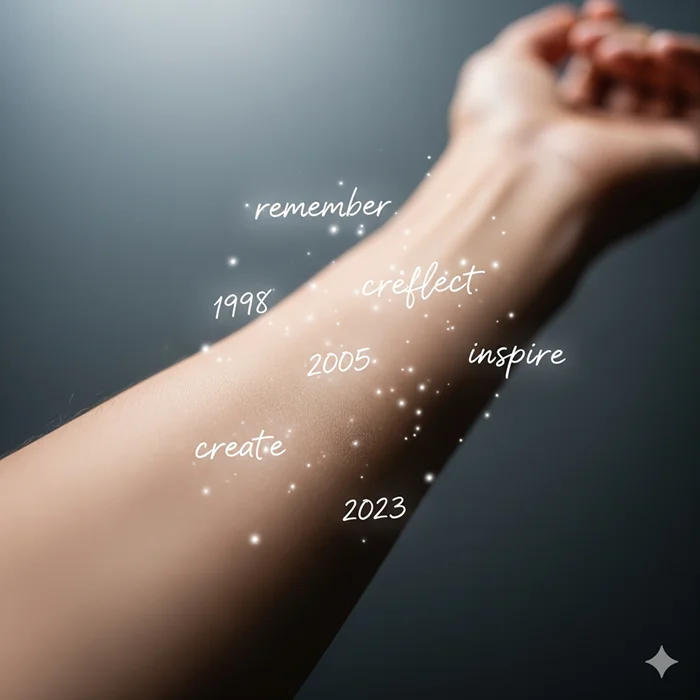
Tattoo SchriftGenerator
Einzigartige Schriftarten für Deko Ideen
Die Wahl der perfekten Tattoo schrift generator ist eine der wichtigsten Entscheidungen bei der Gestaltung Ihres Tattoos. Schriftart, Stil und Design der Schrift verraten viel über Sie. Egal, ob Sie einen Tattoo-Schriftzug oder eine minimalistische Schrift planen – ein Font-Generator hilft Ihnen, die perfekte Schriftart für Ihr Tattoo zu finden. Dieser Leitfaden führt Sie durch die Auswahl der besten Tattoo-Schriftarten, gibt Tipps zur Verwendung eines Font-Generators und zeigt Ihnen, wie Sie einzigartige Schriftzüge erstellen, die wirklich zu Ihnen passen.
Was ist Tattoo Schrift Generator und warum ist sie wichtig?
Die Tattoo-Schrift bezeichnet den Stil oder die Schriftart des Textes, der in einem Tattoo-Design verwendet wird. Ob Zitat, Name oder Datum – die gewählte Schriftart hat einen großen Einfluss auf die Gesamtästhetik des Tattoos genau wie Instagram Schrift. Von kräftigen, dramatischen Buchstaben bis hin zu eleganter Schreibschrift – jeder Stil vermittelt etwas anderes. Es ist wichtig, eine Schrift zu wählen, die zu der Botschaft oder Emotion passt, die Sie vermitteln möchten.
Arten beliebter Tattoo Schriftarten (Fonts)
1. Cursive Tattoo Schrift (Schreibschrift)
Schreibschriften wie Schreibschrift sind eine zeitlose Wahl für Tattoos. Sie verleihen dem Design einen Hauch von Eleganz und Fluss und eignen sich daher ideal für Namen, Zitate oder bedeutungsvolle Sätze. Die durchgehenden Striche handschriftlicher Schriftarten verleihen dem Tattoo eine persönliche, intime Note.
2. Fette und klassische Schriftzüge
Wenn Sie ein Tattoo mit einem besonderen Akzent suchen, sind kräftige Schriftzüge oder Schriftarten mit dicken Linien perfekt. Diese Schriftarten werden oft für aussagekräftige Botschaften oder kurze Zitate verwendet. Die scharfen, kräftigen Linien sorgen dafür, dass das Design auch nach Jahren noch hervorsticht.
3. Vintage- und Old-English-Schriftarten
Für alle, die klassische, zeitlose Looks lieben, sind Old-English oder Vintage-Schriftarten eine ausgezeichnete Wahl. Sie vermitteln ein Gefühl von Geschichte und verleihen dem Tattoo oft ein traditionelles Flair. Diese Schriftart eignet sich gut für Namen, Daten oder Familienwappen.
4. Moderne und minimalistische Schriftarten
Wenn Sie klare Linien und eine moderne Ästhetik bevorzugen, sind minimalistische Schriftarten die beste Wahl. Diese Schriftarten zeichnen sich typischerweise durch scharfe, gerade Linien und einfache Kurven aus, wodurch sie leicht lesbar sind und sich perfekt für alle eignen, die einen modernen Look wünschen.
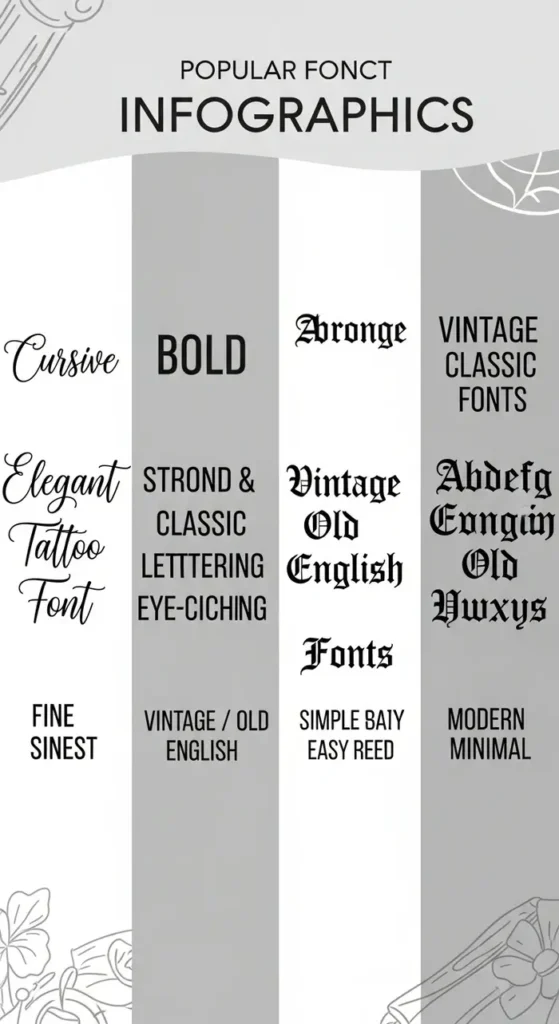
So finden Sie die richtige Tattoo-Schrift mit einem Schriftgenerator
Die Wahl der perfekten Tattoo-Schrift kann eine Herausforderung sein. Unser Online Schriftgenerator vereinfacht den Prozess. So erstellen Sie mit einem Tattoo-Schriftartengenerator das perfekte Tattoo-Design:
1. Verschiedene Schriftarten entdecken
Entdecken Sie zunächst verschiedene Schriftarten und finden Sie heraus, welche Ihnen am besten gefällt. Mit einem Schriftarten-Generator können Sie verschiedene Stile ausprobieren – von handgeschriebenen Schriftarten bis hin zu fetten, modernen Handschriften. Ob Sie Zahlen für ein Datum oder eine schöne Schriftart für einen Namen suchen – mit dem Generator können Sie visualisieren, wie verschiedene Schriftarten auf Ihrer Haut wirken.
2. Design anpassen
Sobald Sie einen Stil gefunden haben, der Ihnen gefällt, können Sie ihn im nächsten Schritt anpassen. Viele Generator-Tools ermöglichen es Ihnen, den Abstand, die Größe und sogar die Form des Textes anzupassen, um Ihr gewünschtes Design zu optimieren. Sie können mit verschiedenen Effekten experimentieren, bis Sie den gefunden haben, der am besten zu Ihrem Text passt.
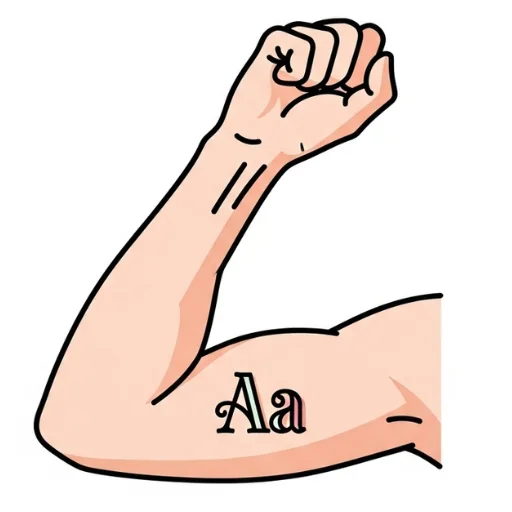
3. Vorschau der Tattoo Schrift Generator
Einer der größten Vorteile eines Schriftgenerators ist die Vorschau Ihres Tattoos vor dem Stechen. Indem Sie sich vorstellen, wie die Schrift auf Ihrer Haut aussehen wird, können Sie bei Bedarf Anpassungen vornehmen, um sicherzustellen, dass das endgültige Design genau Ihren Vorstellungen entspricht.
Best Practices für die Auswahl von Tattoo-Schrift
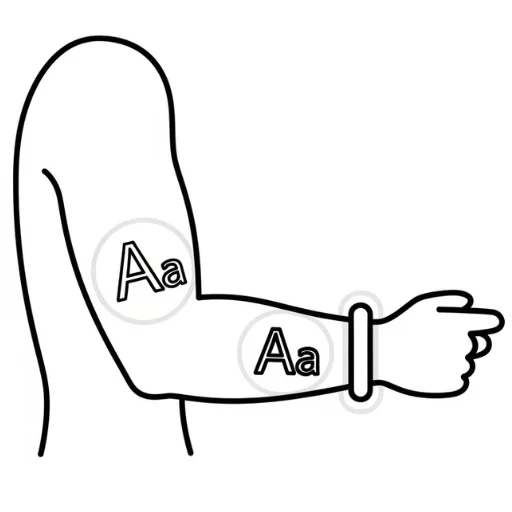
1. Die Platzierung des Tattoos berücksichtigen
Die Position Ihres Tattoos spielt eine große Rolle bei der Wahl der Schriftart. Beispielsweise erfordert ein Tattoo mit Schriftzug auf dem Unterarm möglicherweise größere, kräftigere Schriftarten, während ein dezenteres Design am Handgelenk besser zu zarten Schriften oder handschriftlichen Schriftarten passt.
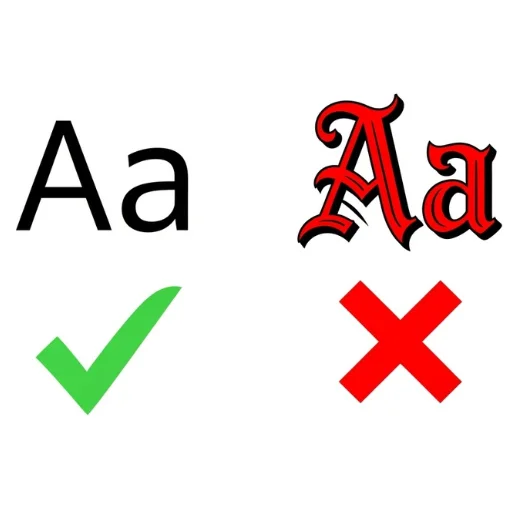
2. Vermeiden Sie zu komplexe Schriftarten
Auch wenn es verlockend sein mag, eine stark stilisierte Schriftart zu wählen, ist die Lesbarkeit entscheidend. Tattoos sollen sichtbar und lesbar sein. Wählen Sie daher eine Tattoo-Schriftart, die ihre Klarheit über lange Zeit behält. Fette Schriftarten altern tendenziell besser, während feine Details in der Schrift mit der Zeit verschwimmen können.